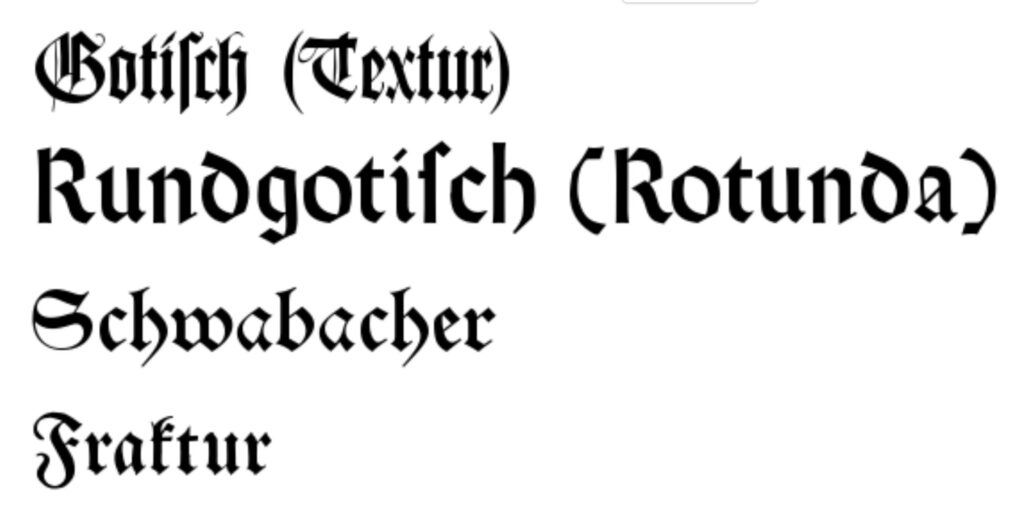
Gebrochene Schriften
Gebrochene Schriften entwickelten sich ab dem 12. Jahrhundert aus der gotischen Minuskel und wurden ab dem 14. Jahrhundert zur dominanten Buchschrift im deutschsprachigen Raum. Ihren Namen verdanken sie den „gebrochenen“ Rundungen. Ihre Verbreitung endete weitgehend im 20. Jahrhundert; ihre Instrumentalisierung durch die Nationalsozialisten belastet ihr Ansehen bis heute. Umgangssprachlich werden sie oft pauschal „Fraktur“ oder „deutsche Schriften“ genannt – die Fraktur ist jedoch nur eine Untergruppe.
Untergruppen:
• Gotisch – stark gebrochene Rundungen, strenges Schriftbild. Beispiele: Fette Gotisch, Wilhelm-Klingspor-Gotisch.
• Rundgotisch (Rotunda) – runder, weicher, weniger streng; vor allem im 14. Jahrhundert in Italien verbreitet. Beispiele: Linotext, Wallau (Rudolf Koch), Weiß-Rundgotisch, Duc de Berry, Clairvaux.
• Schwabacher – ab dem 15./16. Jahrhundert in Süddeutschland; breiter und offener Duktus, charakteristisches rundes o. Häufig in der Lutherbibel verwendet. Beispiele: Renata, Alte Schwabacher.
• Fraktur – ab dem 16. Jahrhundert, schlanker und eleganter als Schwabacher und Rotunda, wurde zur meistgenutzten Druckschrift. Beispiele: Fette Fraktur, Neue Fraktur, Walbaum-Fraktur.
• Fraktur-Varianten – diverse Sonderformen, die sich keiner der genannten Gruppen eindeutig zuordnen lassen.